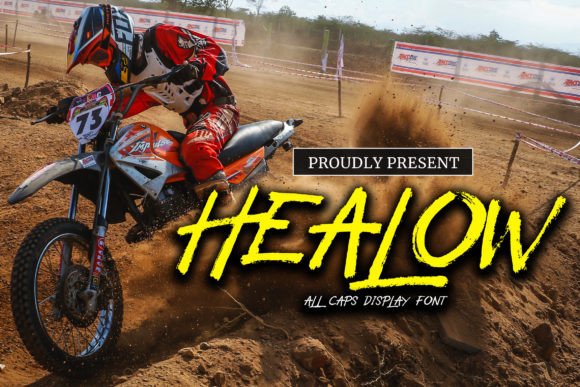
Healow
Якщо ви шукаєте високоякісні ресурси, такі як Healow, цей преміум-пакет є фантастичним вибором для ваших творчих проектів.
Створений з високою точністю, Healow забезпечує чисті вектори, плавну типографіку та комерційну ліцензію для вашого спокою.